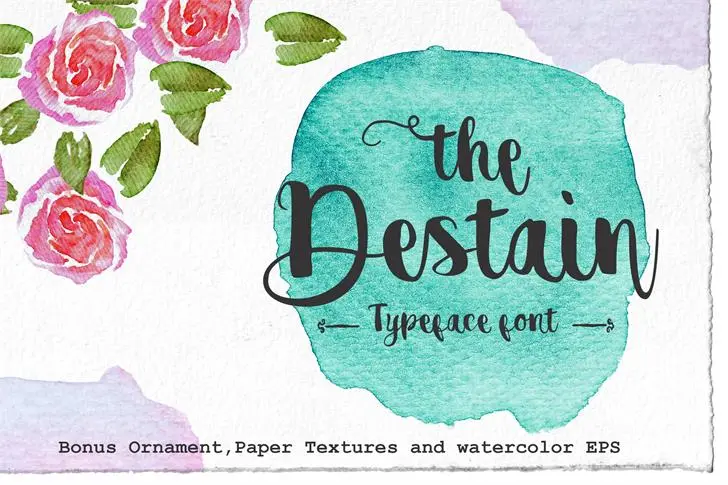
A fonte ‘Destain Script’ é uma criação original inspirada nas ferramentas manuais de canetas à mão livre. Inspirada na ideia de um artesão trabalhando com sua própria mão, essa fonte foi feita para oferecer um estilo elegante e único que se destaca em qualquer projeto. Foi desenvolvida pelo designer Hamilton. Para quem busca algo diferente e autêntico, ‘Destain Script’ é uma opção inovadora. Para baixar a fonte ou usá-la nos seus projetos, visite o site da Creative Market no link fornecido na descrição original: https://creativemarket.com/gungdesta/766353-Destain. Não se esqueça de seguir Hamilton em sua página do Instagram para ficar informado sobre as novidades e seu trabalho futuro: https://www.instagram.com/aris_aka_greataris/. Sinta-se à vontade para explorar os recursos criativos disponíveis neste design exclusivo.